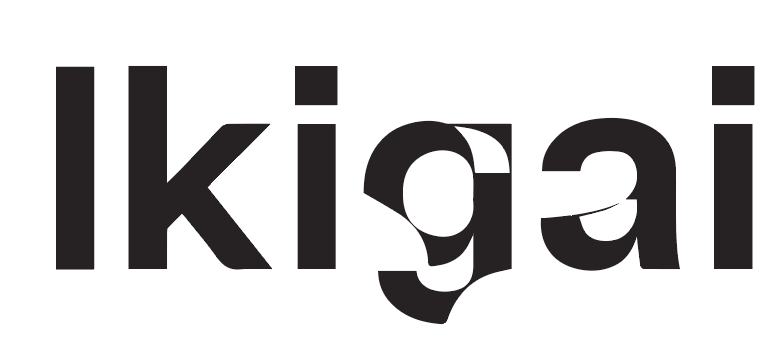
Schrift mit Aussparung gesucht
Ich bin aktuell auf der Suche nach der Schrift im Anhang. Sie zeichnet sich durch diese experimentellen Aussparungen im g und a aus. Leider finde ich sie nicht mehr. Ich bin dankbar um jeden Hinweis!